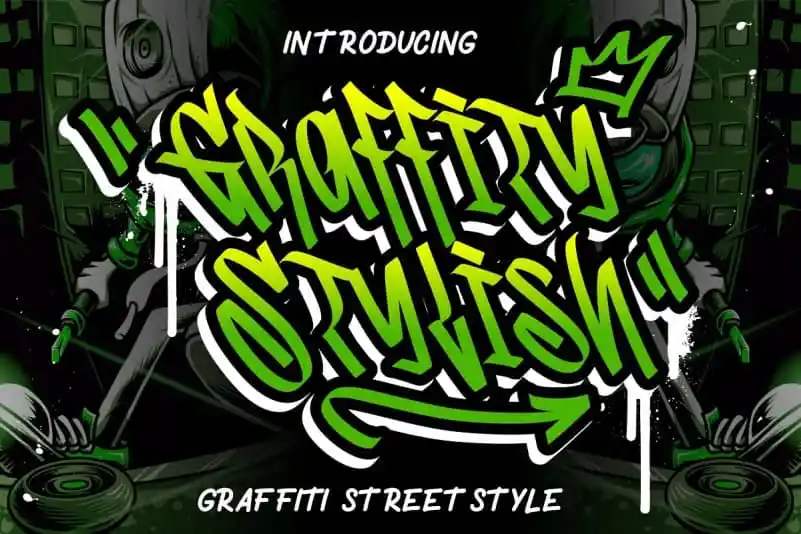
Graffity Stylish Display Font – Download Grátis
A Graffity Stylish Display Font é uma mistura de graffiti moderna com estilo elegante, criada pela Creatype Studio para quem procura uma fonte que represente a street style contemporânea. Inspirada no entusiasmo e na vitalidade dos grafites urbanos, essa fonte oferece um equilíbrio entre o vibrante e o sofisticado, perfeitamente adaptável para criações de design gráfico em alta resolução. Este tipo de letra é ideal para aplicar em logotipos, websites ou publicações digitais que buscam um toque único e vibrante, seja ele em grandes tamanhos para criar uma forte impressão visual, ou em pequenos detalhes para dar vida a qualquer projeto design. Seja você criando novas marcas ou simplesmente adorando o estilo de rua, essa fonte está aqui para ajudar a expressar sua ideia de maneira autêntica e moderna.